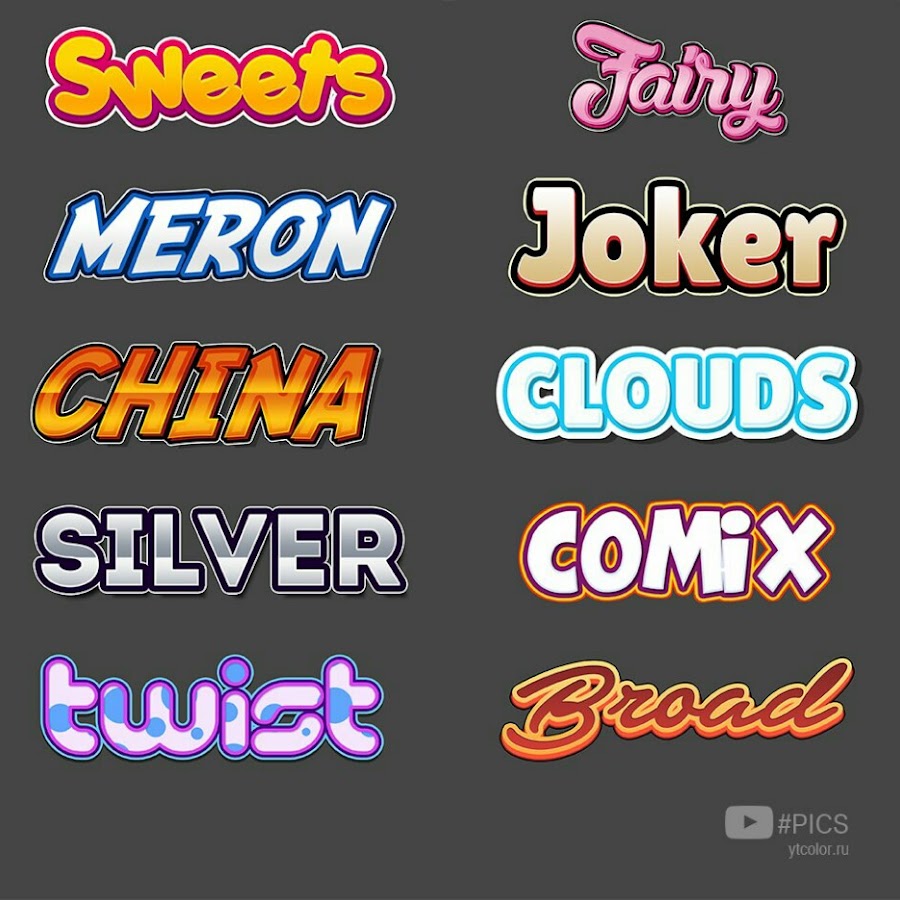
Как правильно выбрать шрифт для игры
Дуг Стюарт из Kongregate написал о том, как придать индивидуальность игре при помощи шрифта и о том, как сделать это правильно.
Один из самых простых способов придать некоторую индивидуальность вашей игре — использовать уникальный шрифт. Это также один из самых простых способов улучшить или ухудшить юзабилити вашей игры. Но для выбора правильного шрифта требуется совсем немного. Оставайтесь с нами и узнайте все об этом!
Основы, которые вам надо знать
Сложность гарнитуры обманчива, так что давайте разберемся с основами. Во-первых .давате посмотрим на параметры шрифта:
Некоторые из них являются более загадочными и по-настоящему используются только в типографиях, но другие очень важны для выбора шрифта. Особое внимание стоит обратить на x-height и я рассмотрю ее значение ниже.
Также обратите внимание на засечки – это то, что люди имею ввиду, когда говорят о Sans Serif, slab serif и serif шрифтах. Примеры каждого вы можете увидеть ниже:
[notice]Шрифты slab serif — это класс шрифтов, у которых серифы имеют форму пластин (то есть широких линий или прямоугольников). Шрифты slab serif часто, но не всегда, легко читаются. Поскольку серифы простые и строгие, они создают ощущение того, что символы «вбиты» в страницу.[/notice]
Еще важно иметь в виду различие между дисплейным шрифтом, шрифтом текста и шрифтом сноски. Посмотрите ниже:
Как вы можете видеть, есть тонкие различия в зависимости от того, для каких целей создавался шрифт. Дисплейный шрифт предназначен для больших надписей и таким образом, как правило, имеет более тонкие черты или сложные конструкции. В тексте обычно избегают этого, предпочитая ясность в стандартных для чтениях размерах. Шрифты сносок предназначены для маленьких текстов, таких как сноски (сюрприз!), титры и других мелких надписей, поэтому, как правило, у них больше x-height.
Это был лишь краткий обзор, гораздо больше вы можете узнать самостоятельно, если вам это интересно.
На что смотреть, выбирая шрифт
Вы должны быть в состоянии ответить, какой шрифт будет использоваться для чего, какой стиль вы ищете, какие другие элементы на экране нужно отобразить в выборе шрифта.. Вы можете зайти довольно далеко, так что дадим общие рекомендации по выбору гарнитуры.
О каком временном периоде будет игра?
Ваша игра про средневековье или про космос? Она происходит на Диком западе или в мире стимпанка? Стиль шрифта передает определенное настроение и является отличным способом углубить тему вашей игры и придать ей некоторую индивидуальность. К счастью, вам не надо быть экспертом чтобы понимать, что один шрифт представляет научную фантастику, а другой выгладит очень старомодно.
Эти шрифты очень стилизованы, но вам заходить так далеко не обязательно. В простейшем случае, шрифты с засечками всегда чувствуются старше. Причина этого заключается в том, что они разрабатывались поколениями до нас. Sans-serif шрифты всегда ощущаются современными или футуристическими, так как, собственно говоря, они новое явление, возникшее в конце 19 века.
Если у вас возникли проблемы с описанием стиля, который подошел бы вашей игре, я полагаю вам для вдохновения следует посмотреть на то, что делают остальные. Посмотрите на игры, которые вы любите и критически осмыслите их выбор шрифта – это поможет вам сделать собственный выбор. Я также считаю, что взгляд на обложки книг, постеры кинокартин и заголовки это прекрасное начало для поиска формы вашего текста на экране.
Если вам нужны примеры, то я привел их в конце, вот три источника, которые я бы рекомендовал:
Какой текст я буду использовать вместе с этим шрифтом?
Может быть, вы ищите что-то для своего логотипа, в этом случае вы можете выбрать практически любой шрифт, будь то очень простой или очень сложный. Так как он в основном будет отображаться в больших размерах, вам не надо слишком беспокоиться о том, как разные тонкие детали будут выглядеть съёжившись.
С другой стороны, если вы собираетесь использовать гарнитуру в тексте, то вам следует избегать использования богато декорированных шрифтов и вместо этого сосредоточиться на примерах с чистыми, четкими линиями. Это тот момент, когда вам надо уделить повышенное внимание на x-height шрифтов. Большая x-height, где высота букв приближается к высоте прописных букв, проще читается по сравнению с маленькими x-height.
На каких языках будет моя игра?
Может быть, вы планируете выпустить игру только на своем родном языке, или, возможно, вы собираетесь выпустить ее на десятках языков. Если вы планируете переводить игру, очень важно посмотреть на набор символов шрифта и дважды проверить поддержку языков. Действительно хорошо разработанные шрифты, такие как Open Sans, имеют прекрасную поддержку языков для большинства романских алфавитов. К сожалению, вы вряд ли найдете один шрифт, покрывающий всея языки – если вы захотите выйти за пределы латиницы и использовать кириллицу или языки Азии.
Мой главный совет
Этот шрифт разработан для киберспортивных команд. Он имеет современный дизайн букв, который позволит вам создавать логотипы, значки и другие рисунки для профессионального продвижения ваших киберспортивных команд.
Вы можете использовать этот бесплатный шрифт для создания современных и привлекательных заголовков для ваших игровых каналов и социальных профилей.Шрифт содержит как прописные, так и строчные буквы.